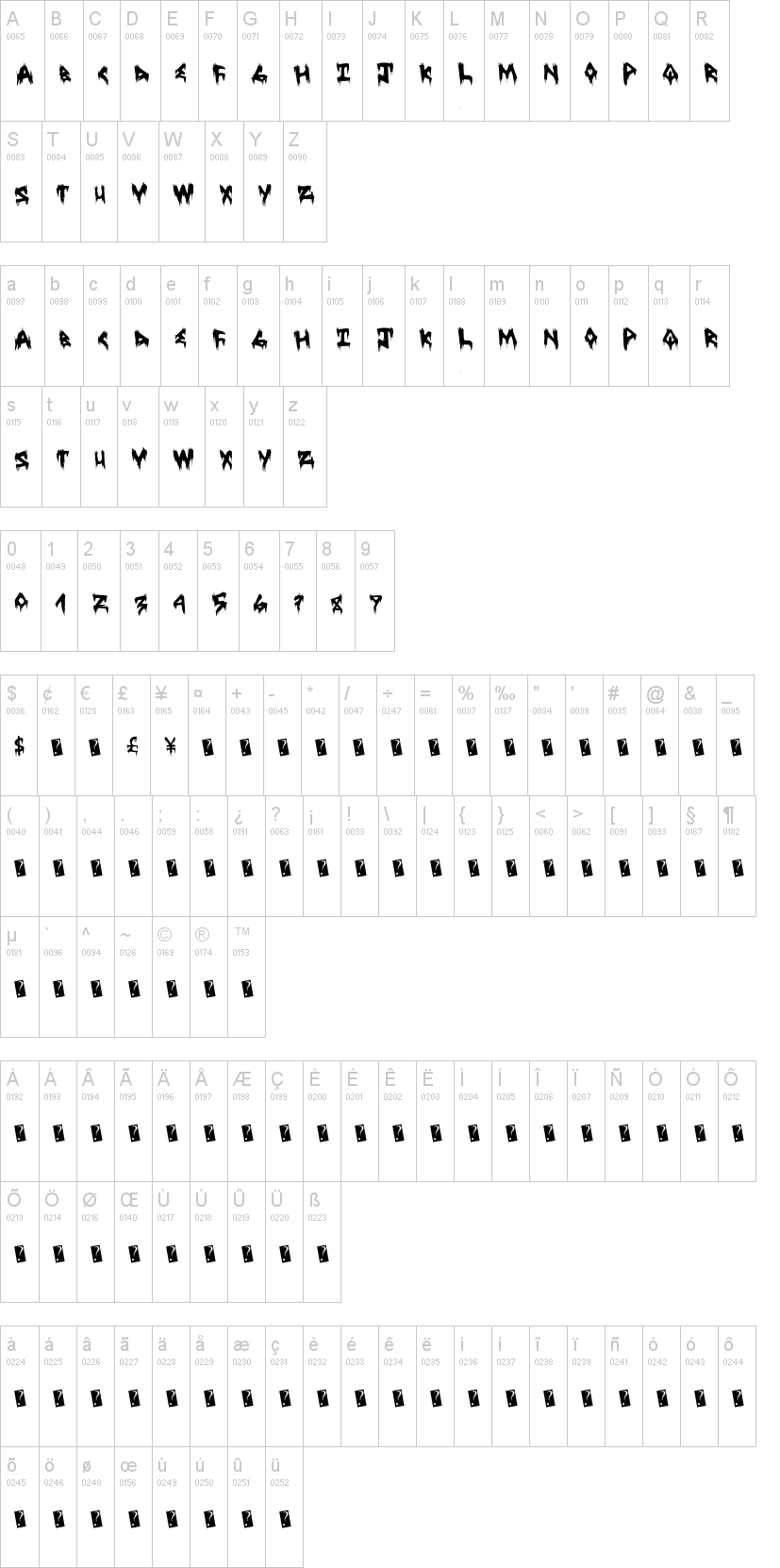
Treehaus Horror
Treehaus Horror 是一款有着可怕外观的英文字体,它采用了粗犷的线条,创造出一种恐怖的视觉效果,这种字体可以用来制作海报、海报、广告、标题等。它有着独特的设计风格,可以带给你一种恐惧感,可以在不同的场合中使用,比如游戏、电影海报、T恤、网页等。
Treehaus Horror是一款非常不错的手写艺术字体,具有很好的视觉感,适合于文化类的宣传设计、商业类品牌的广告和产品包装设计以及个性化文字排版等较多场景。